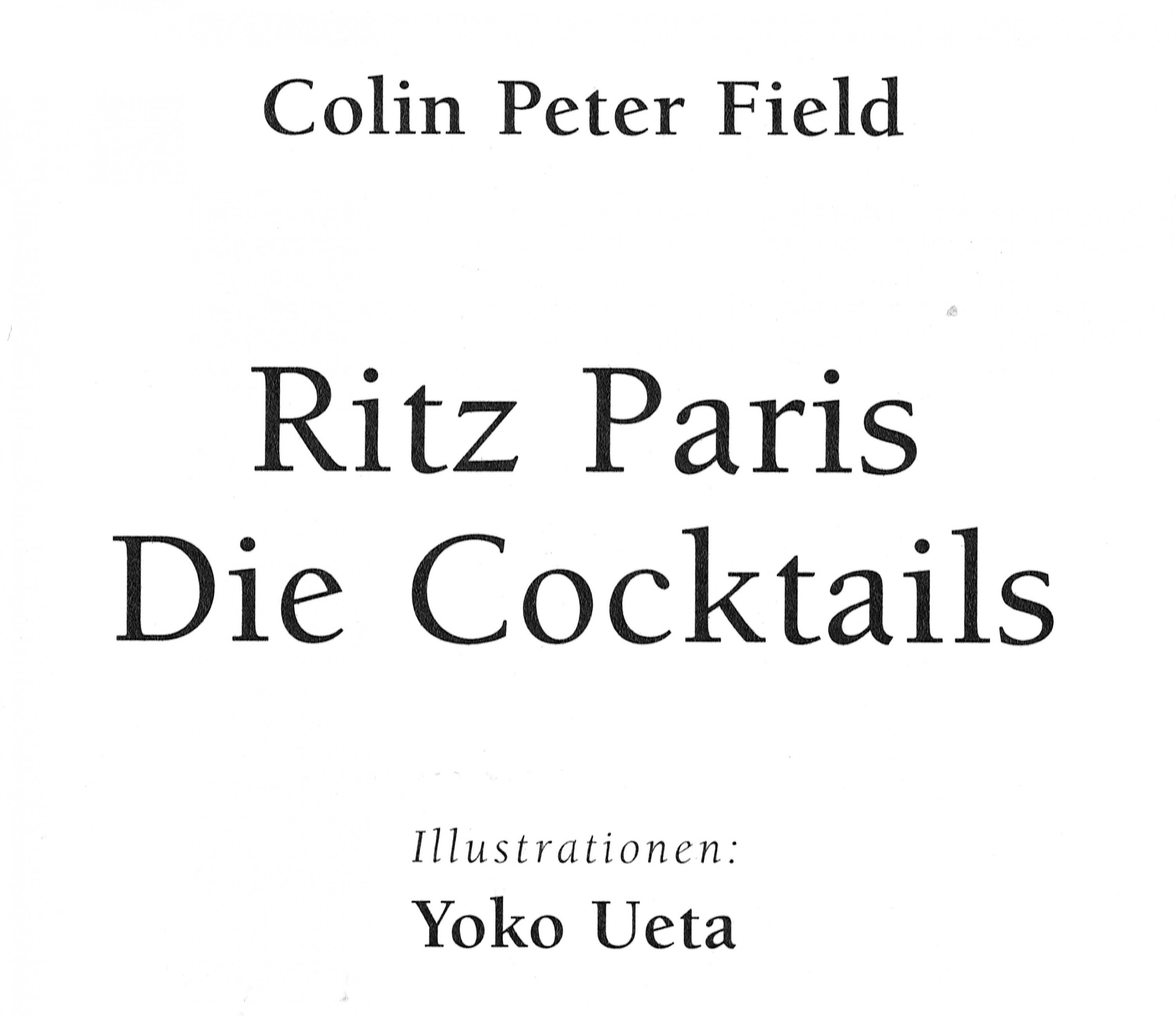
Suche Schriftart(en) aus einem Cocktail-Buch von 2001
Mein erster Post in diesem wunderbaren Forum, in dem ich schon lange mitlese und tolle Inspiration gefunden habe (vielen Dank dafür)! Nun hoffe ich auf das fachkundige Auge der Experten bei der Suche nach der Schriftarten-Familie, die in diesem hübschen Büchlein verwendet wird:
Da die Vorschau vorstehender Links wohl zu unscharf ist, habe ich den Titel und ein paar Textzeilen aus der deutschsprachigen Ausgabe gescannt und natürlich auch schon bei WhatTheFont gesucht. Beim Titel schlug WhatTheFont u.a. die Birca Semibold von Linotype vor, aber so ganz passt das noch nicht, auch die Birka Roman wirkt im Textbild auf mich "langweiliger". Mit etwas längerem Fließtext war die Schriftartenerkennung bei WhatTheFont ergebnislos.
Im Buch selbst wird die Schriftfamilie leider nicht erwähnt. Verlag ist Les Éditions du Chêne, Hachette Livre, 2001, die (im Layout identische) deutsche Ausgabe erschien 2003 bei Delius, Klasing & Co. Das Layout besorgte übrigens Sabine Houplain, offenbar die Directrice Artistique des franz. Verlags.
Zusatzfrage: Mit welchem Begriff würde man diese Schrift denn klassifizieren?
Edit: whatfontis.com schlägt ITC Berkeley Old Style vor - sieht nach 'nem Treffer aus, oder? Ich vermute, im Titel "Medium", im Fließtext Book? Dazu sind im Buch noch verschiedene Italic-Schnitte.
whatfontis.com schlägt ITC Berkeley Old Style vor - sieht nach 'nem Treffer aus, oder?